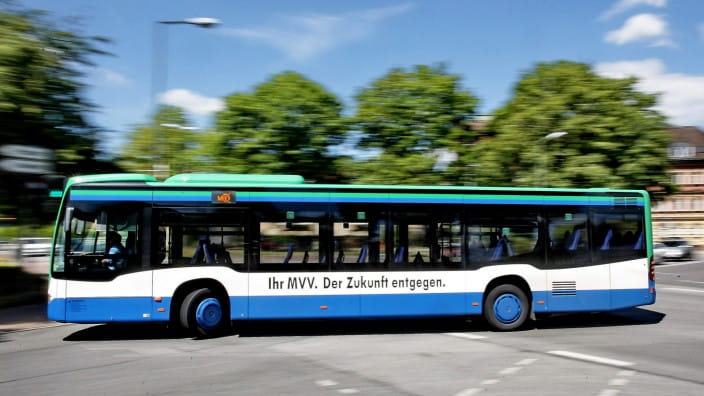
Welche Schriftart verwendet der MVV an der Seite der Busse?
• Servus, die Schriftart/Font nennt sich "Futura Condensed", meistens in "Bold", also Fettschrift.